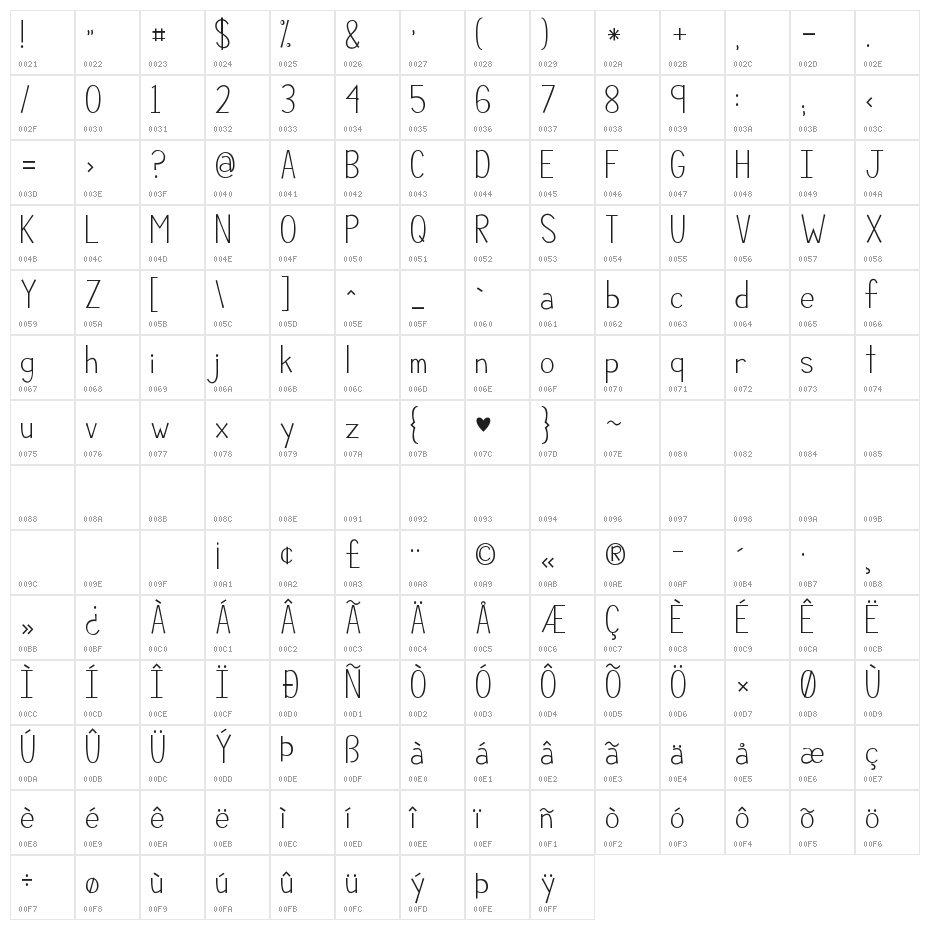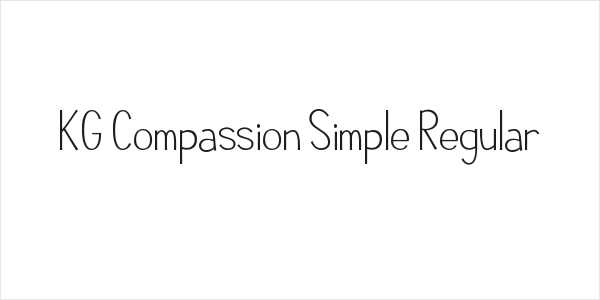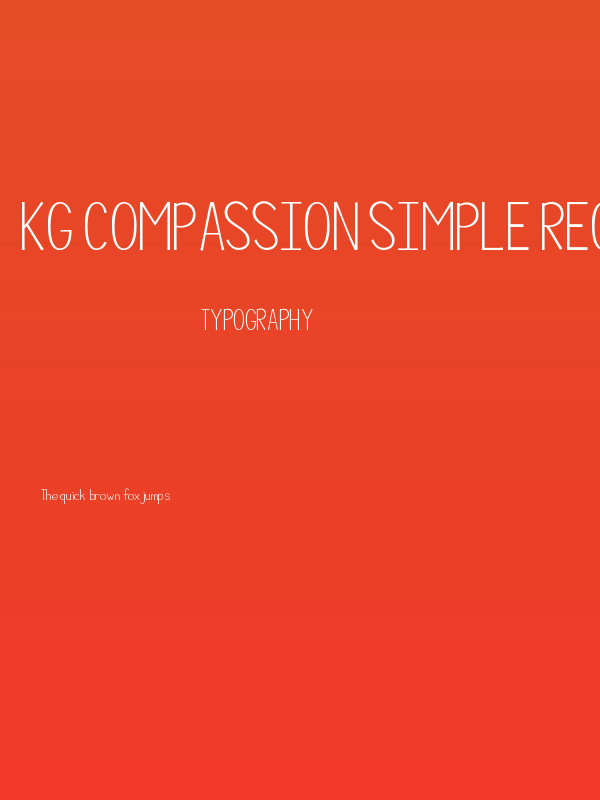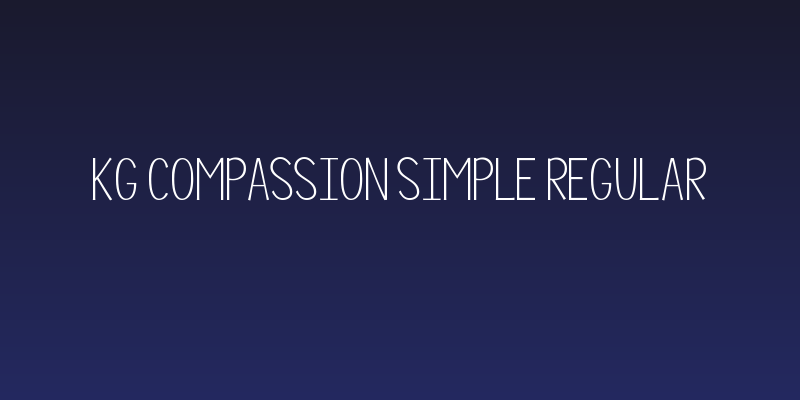
KG Compassion Simple Regular Font
| Anwendungsfall | Headlines, Body text, Logos |
| Vorgeschlagene Projekte | Ideal for minimalist branding, modern websites, and clean editorial layouts. |